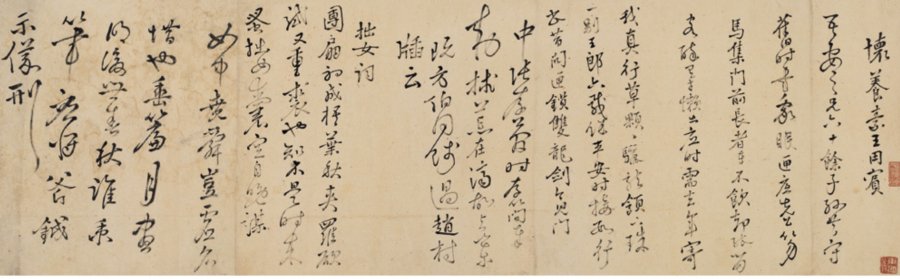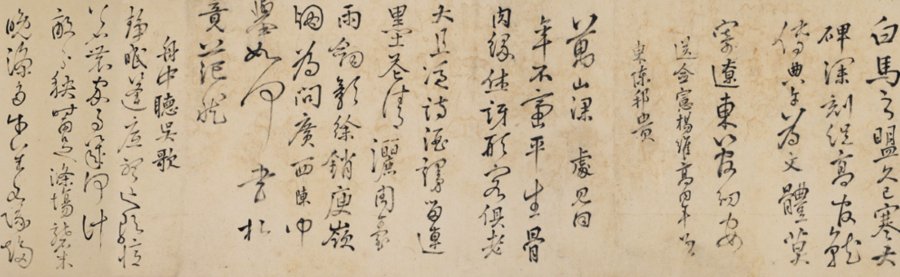
张弼一位喜醉书的明代书法家
张弼(1425~1487)字汝弼,家近东海,故号东海,晚称东海翁。松江府华亭县(今上海松江)人。明宪宗成化二年进士,久任兵部郎,议论无所顾忌,出为南安(今江西大余)知府,律己爱物,大得民和。长于诗文,草书甚佳,被评为“颠张复出”。尝自言吾书不如诗,诗不如文,著有《东海集》。